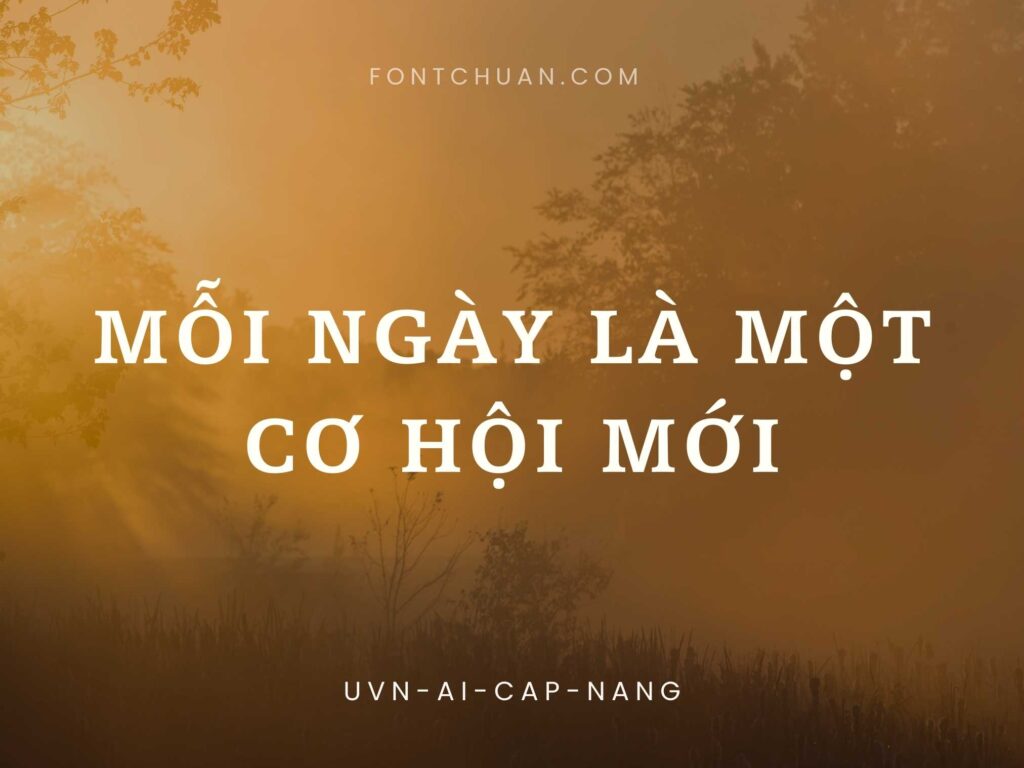
Font UVN Ai Cap Nang Việt Hóa
UVN Ai Cập Nắng là một kiểu chữ độc đáo mang phong cách Ai Cập cổ đại, với các đường nét mạnh mẽ và hình dạng đặc trưng gợi nhớ đến chữ viết trên các công trình kiến trúc cổ. Font này có sự kết hợp giữa các nét dày và mỏng, tạo nên sự tương phản cao, giúp nó trở nên ấn tượng khi sử dụng trong thiết kế tiêu đề hoặc các dự án sáng tạo liên quan đến lịch sử và văn hóa.
Font UVN Ai Cập Nắng được sưu tầm và chọn lọc bởi các thành viên của Font Chuẩn nhằm mang đến cho người dùng một lựa chọn độc đáo khi thiết kế. Với phong cách đặc trưng, font này phù hợp để ứng dụng trong các dự án thiết kế liên quan đến chủ đề lịch sử, quảng cáo, biển hiệu và nhận diện thương hiệu. Đặc biệt, nó có thể được sử dụng trong ngành thiết kế giáo dục hoặc bất động sản để tạo điểm nhấn cho nội dung. Nếu bạn đang tìm kiếm một kiểu chữ đậm chất cổ điển và mạnh mẽ, UVN Ai Cập Nắng là một lựa chọn đáng cân nhắc.